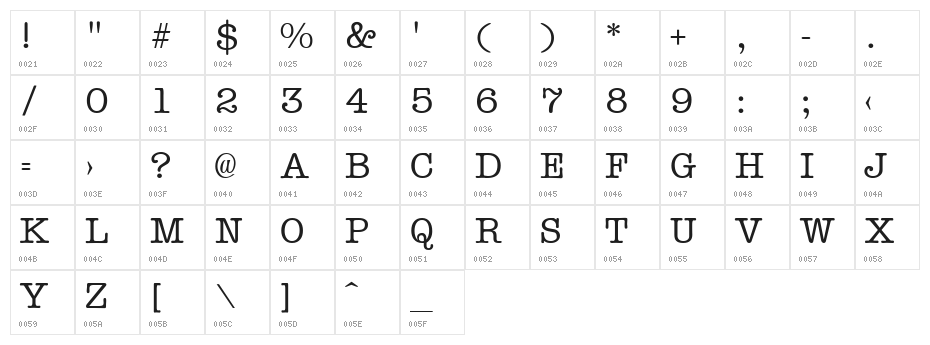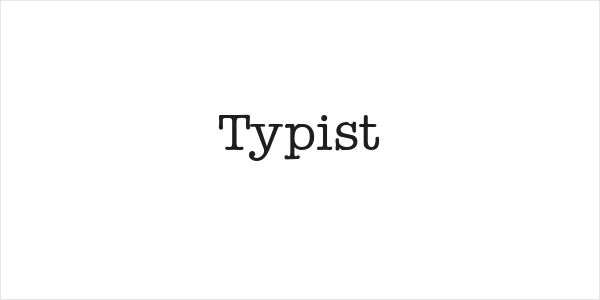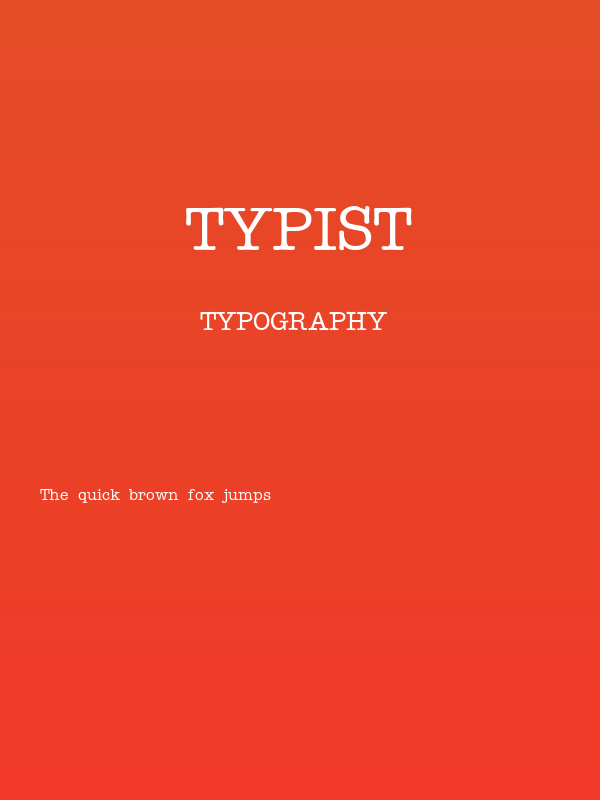
Typist Font
✎ Typewriter
| Gesamtstil | Vintage |
| Anwendungsfall | Headlines, Body text, Logos |
| Vorgeschlagene Projekte | Ideal for vintage-themed designs, typewriter simulations, and creative projects evoking nostalgia. |